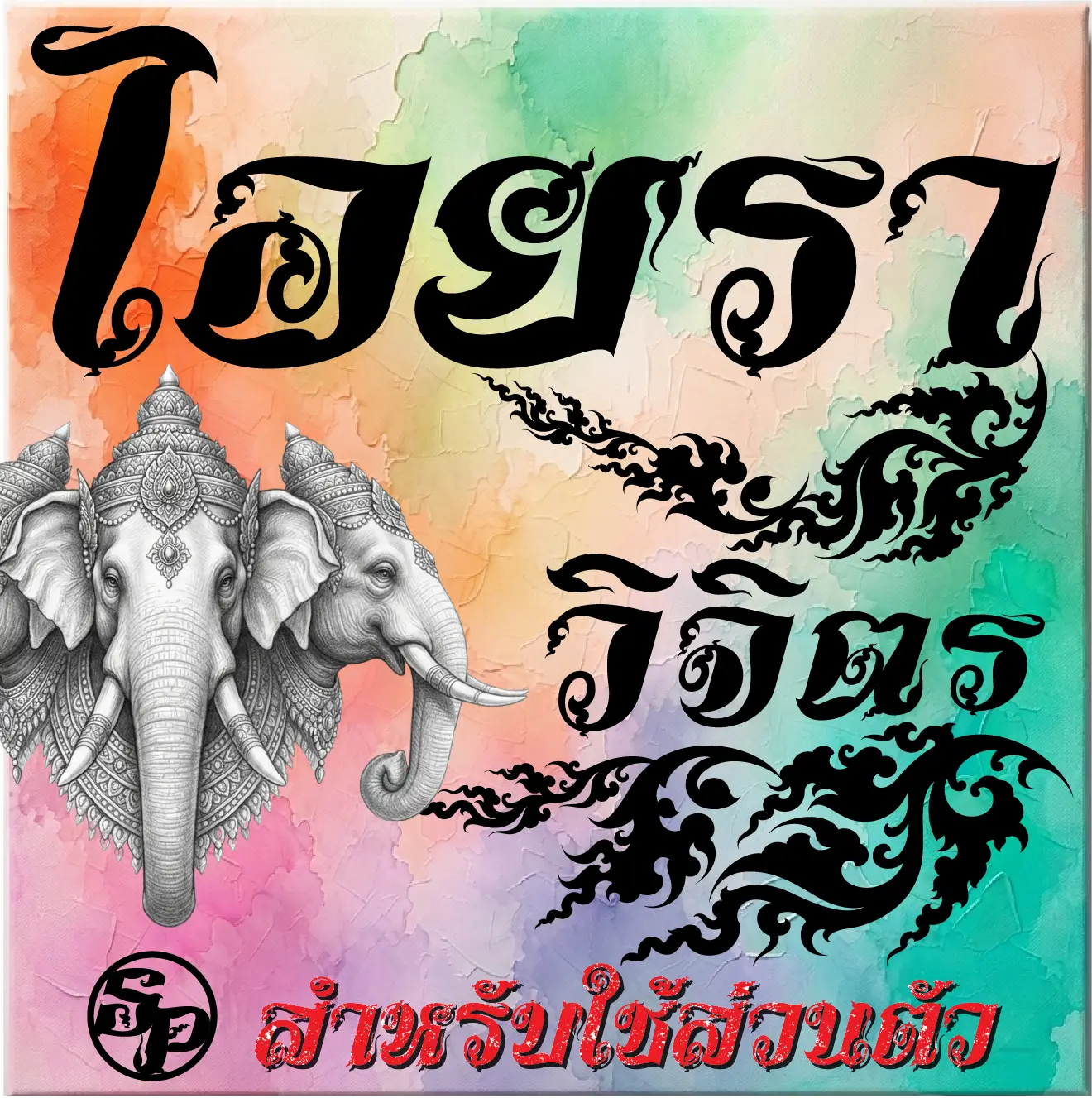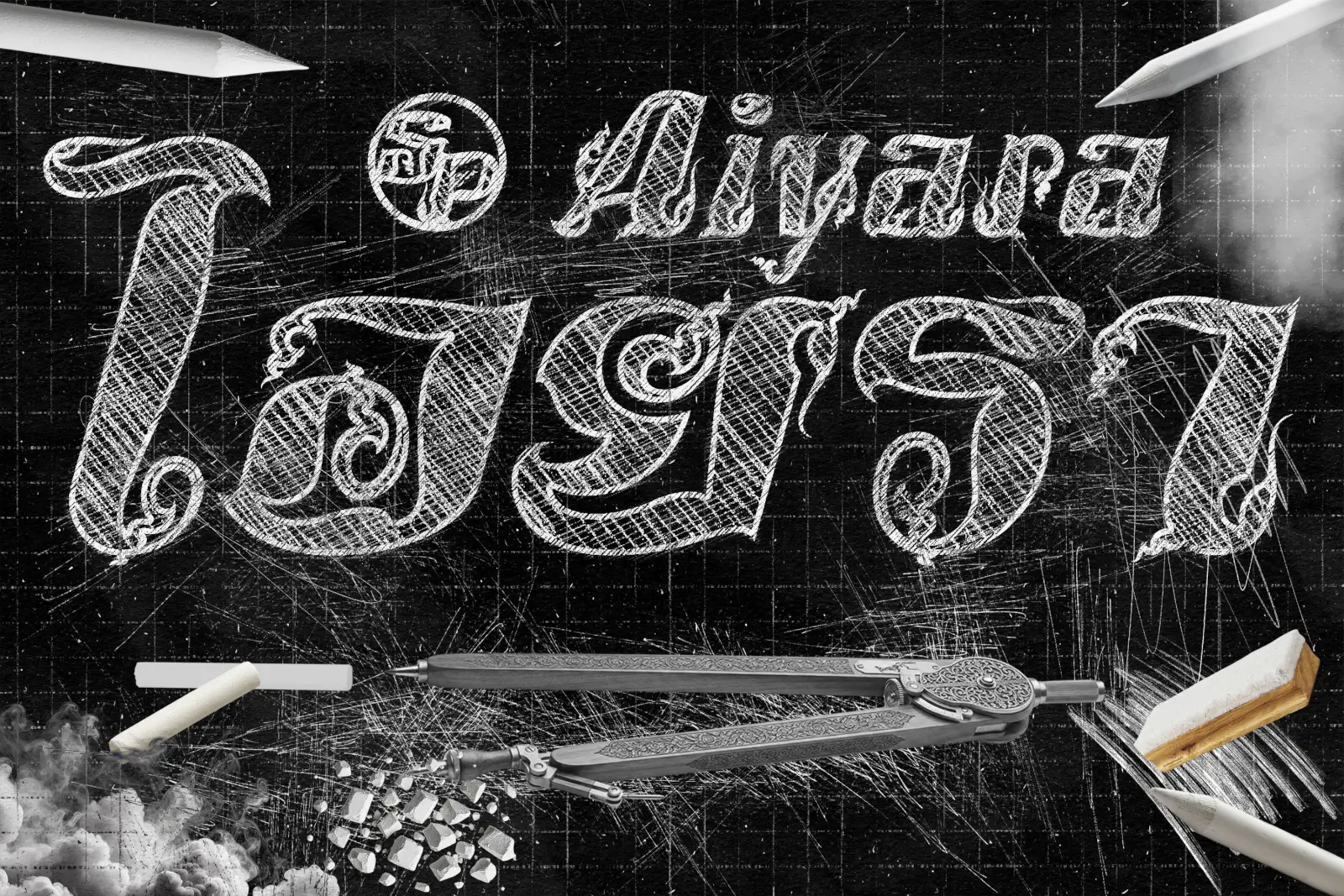
ไอยรา (SP_Aiyara) – โหลดฟรี! อนุญาตให้ใช้งานเฉพาะส่วนตัวเท่านั้น (personal use) สำหรับการทดลอง-งานออกแบบสื่อสิ่งพิมพ์โฆษณาต่างๆ รองรับทุกแพลตฟอร์ม
SP_FONT อักษรวิจิตร มุ่งเน้นสู่คุณค่าเอกลักษณ์ความเป็นไทย ใส่ใจทุกเส้นสายรายละเอียดศิลป์
ไอยรา (SP_Aiyara)